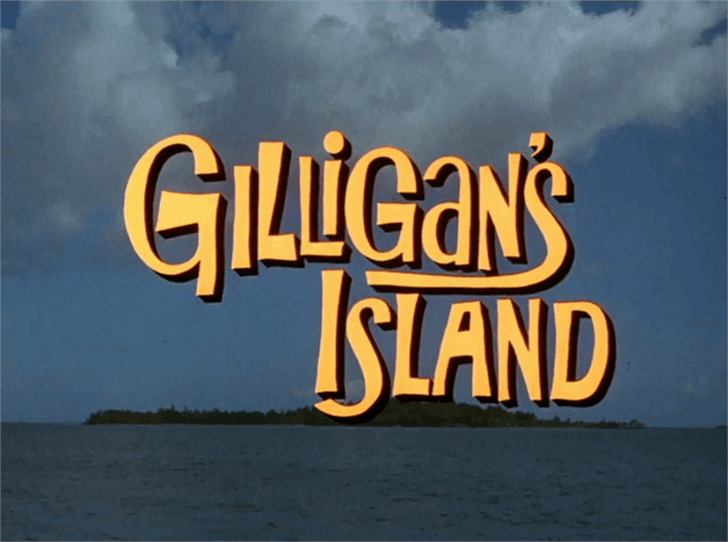
A fonte “Gilligans Island” foi criada baseada no famoso programa de televisão por razões óbvias. Esta fonte é uma recriação meticulosa dos elementos gráficos icônicos usados nos créditos iniciais e na logo principal do show. O designer Hamilton, com seu trabalho árduo, transformou esses materiais em um verdadeiro conjunto de ferramentas digitais que pode revolucionar a aparência de seus projetos. Perfeita para uso em textos a grande escala, esta font é ideal tanto para documentos quanto para aplicação em arte digital como cartazes e adesivos. Ela consegue transmitir com precisão o espírito tropical e descontraído daquela divertida série marinha dos anos 1960, oferecendo um aspecto animado e informativo sem perder a essência do design original. Seja você um designer de arte digital ou um criador de grafismo urbano, “Gilligans Island” é uma escolha inegável para dar vida à sua ideia com um toque memorável e reconhecível.